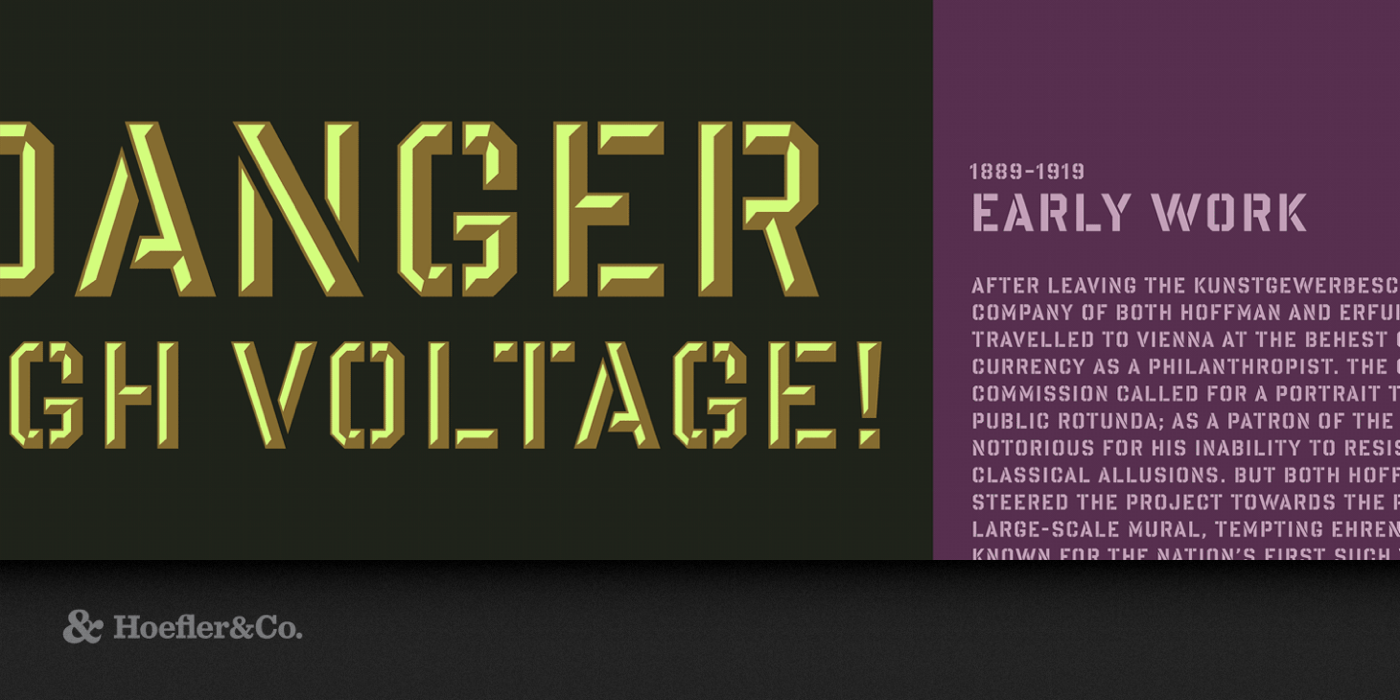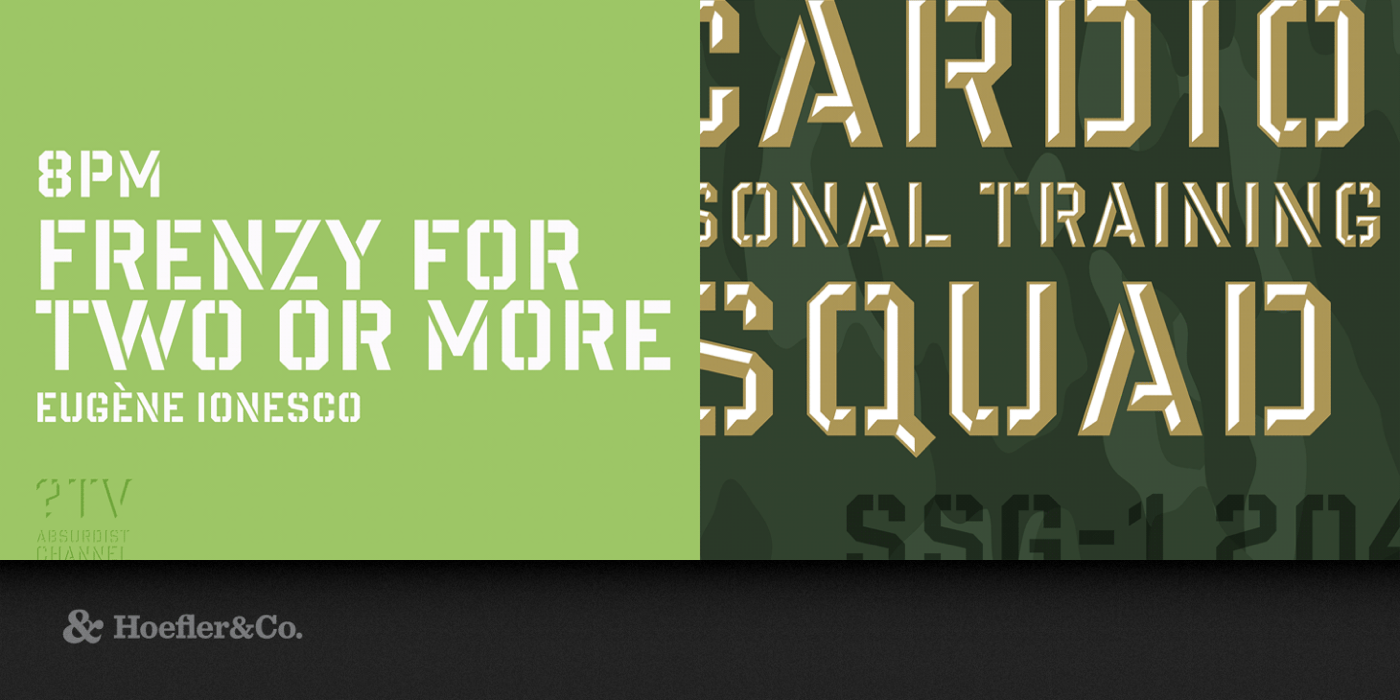
Die Giant ist eine Ebenenschrift von Jonathan Hoefler. Mit den Schnitten »Layers Highlight« und der »Layers Background« kann die Schrift zweifarbig gesetzt werden. Die »Regular« kombiniert beide Schnitte zu einer lichten einfarbigen Version.